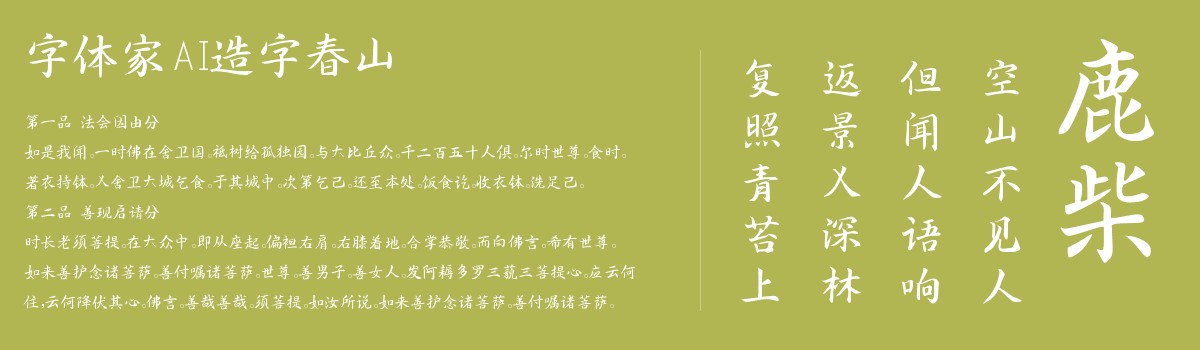
字体家AI造字春山
字体家AI造字春山是一款由字体家AI神笔造字生成的艺术字体,这款字体横画细劲,两端带圆润衬线,如嫩芽初绽;竖画粗壮沉稳,线条饱满如山峰。撇捺由粗渐细,收笔尖柔舒展,似山间流云。转折处方正中透着柔和,整体结构端庄协调,兼具规整与灵动,笔画力度均匀,典雅温润。适合用于一些广告标题、平面文案、海报标题、网页广告用字的编辑。